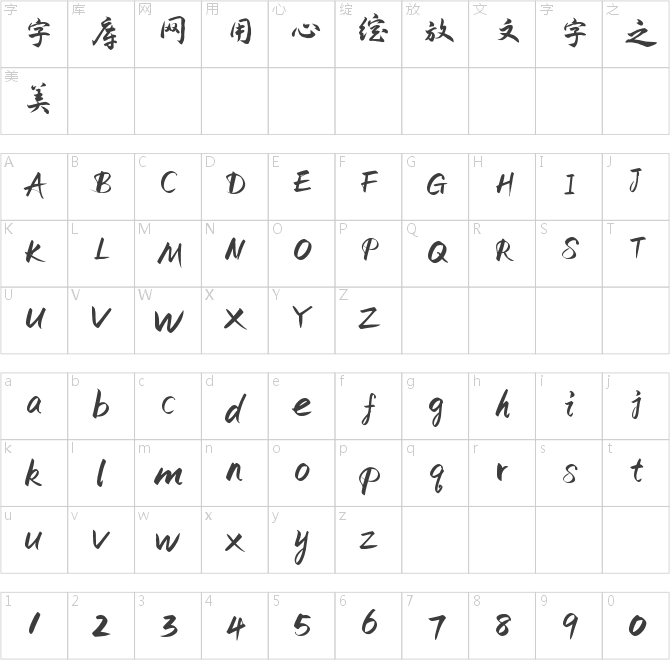
字體名稱: 演示夏行楷
字稿作者:劉錫棟
中國漓江書畫藝術家協會理事丨北京中國書畫研究院研究員丨中國民族硬筆書法家協會會員丨中國楹聯學會會員丨黑龍江楹聯家協會會員丨高級政工師,已退休
字體制作:人生哥(和他的半自動電腦)
演示夏行楷字體Slidexiaxing字庫是一款讓人賞心悅目、百看不厭的中文字體,適合各類廣告和產品包裝設計應用,字體大小9.61MB,格式為ttf字體,上傳用戶是董志高,作者/版權方為演示